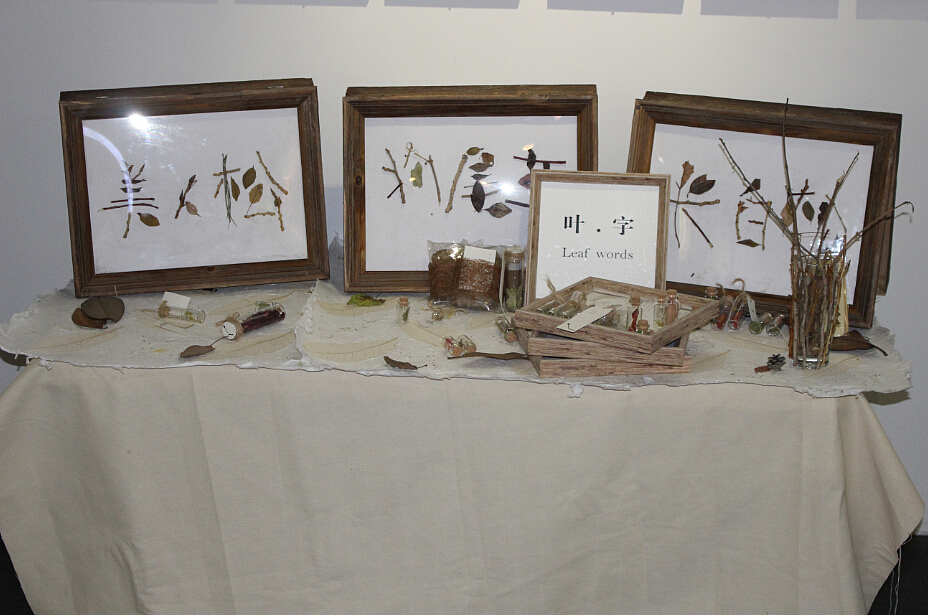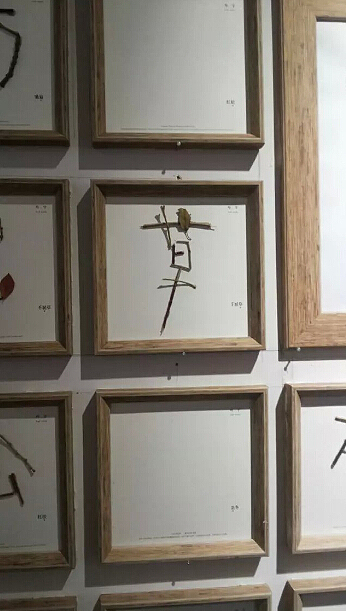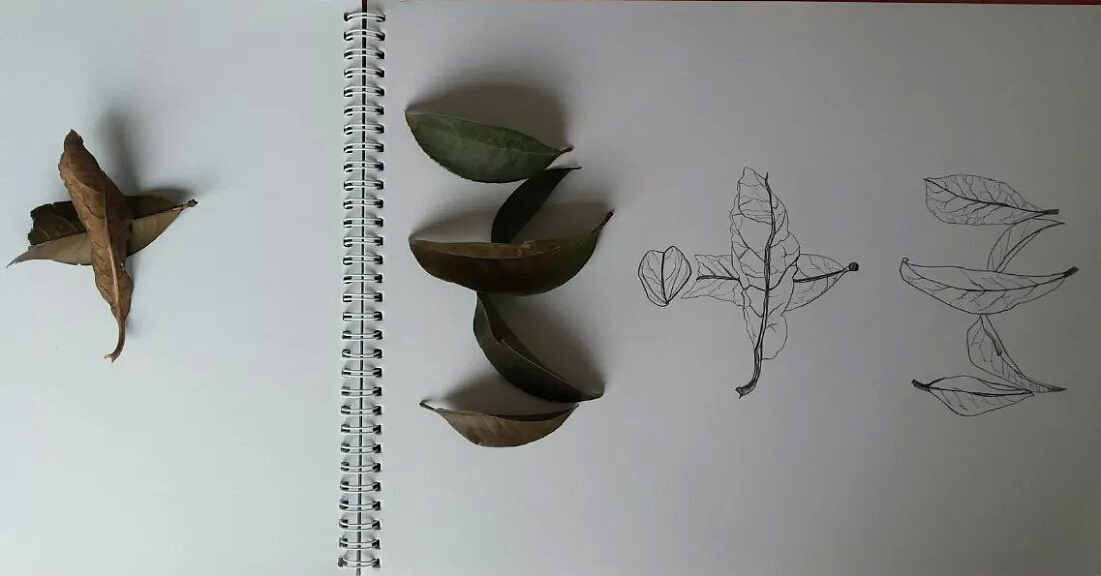
《叶 字》
2015.6.27 毕业设计《叶 字》
不知情之所起 一往情深
我喜欢叶子,因为叶子是天然,也是常见的,常见中的美不易被发现,但一旦发现的,会觉得叶子的世界是一个很神奇的世界,你会被叶子所创造的世界所惊叹!
于是我以叶子为元素,进行我的字体设计。
在南湖公园捡的叶子,好喜欢叶子哦,我滴灵感来源,O(∩_∩)O哈哈哈~